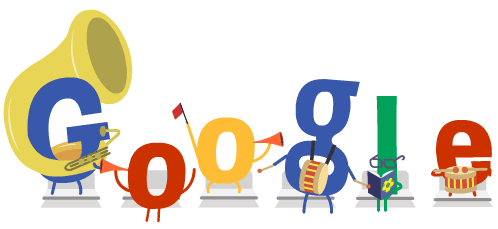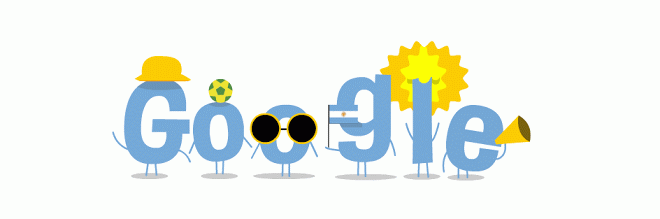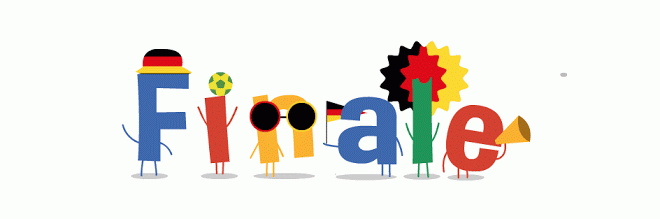
Google Doodle WM-Font
Nachdem die Fußball-WM heute dem Ende zugeht, werde ich die erfrischenden Google Doodles der letzten Tage vermissen, vorallem aber wird mir der Font in Erinnerung bleiben ... kennt den jemand?
Sofern er nicht handgemacht ist, scheint er ein alternatives g zu besitzen.